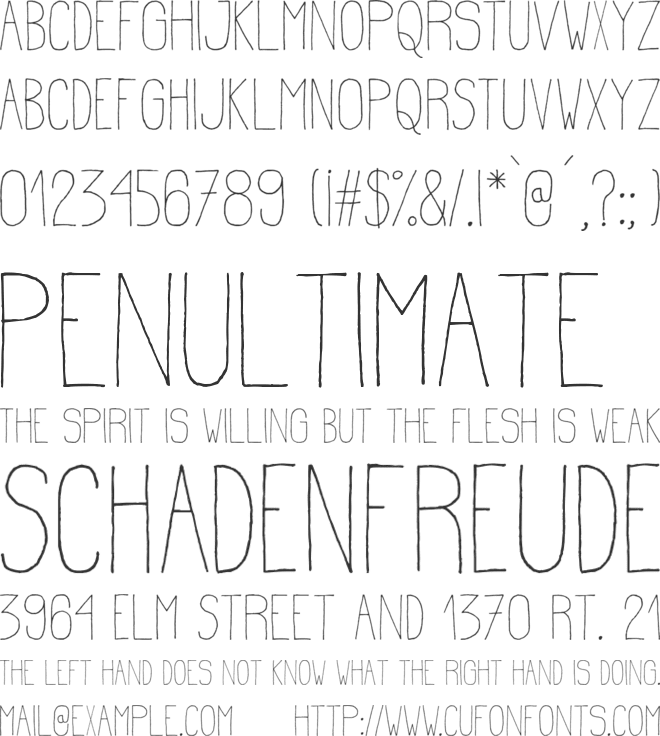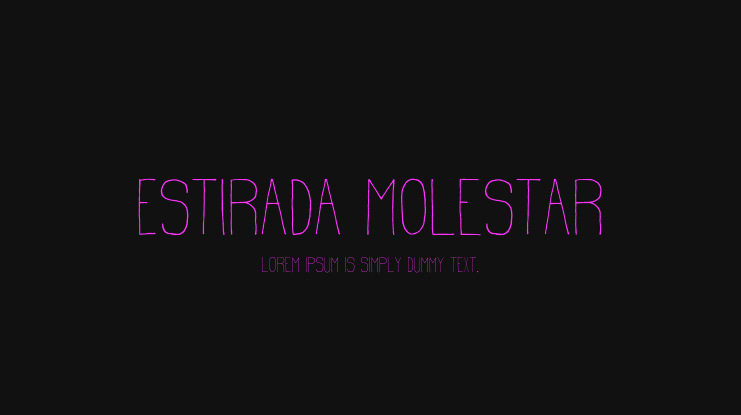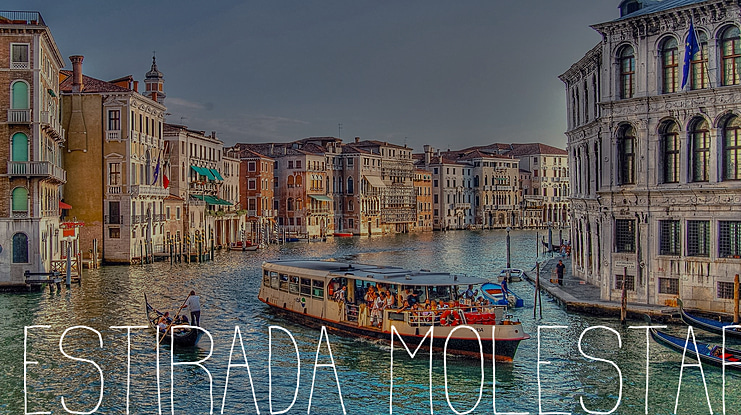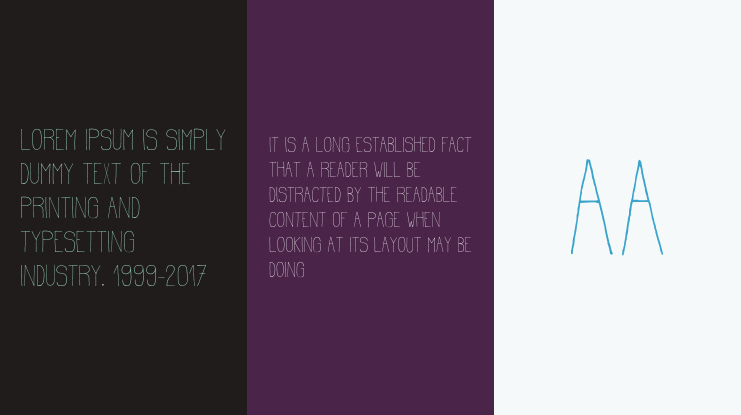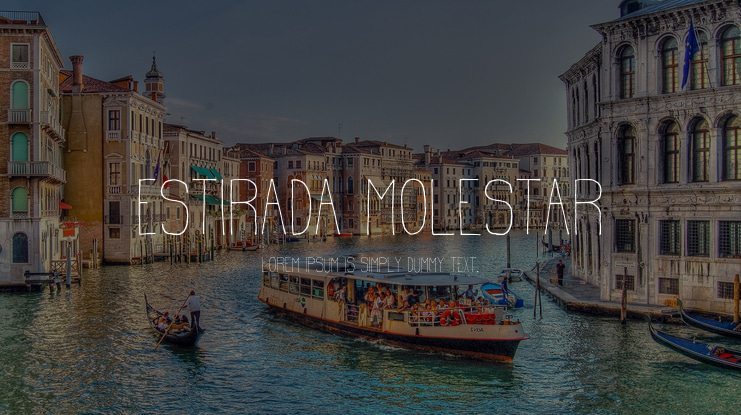
Estirada Molestar Font
Fuente creada para el fanzine "Manual práctico para eliminar la publicidad de tu vida" (http://www.molestar.org/2013/08/09/manual-practico-para-eliminar-la-publicidad-de-tu-vida/)